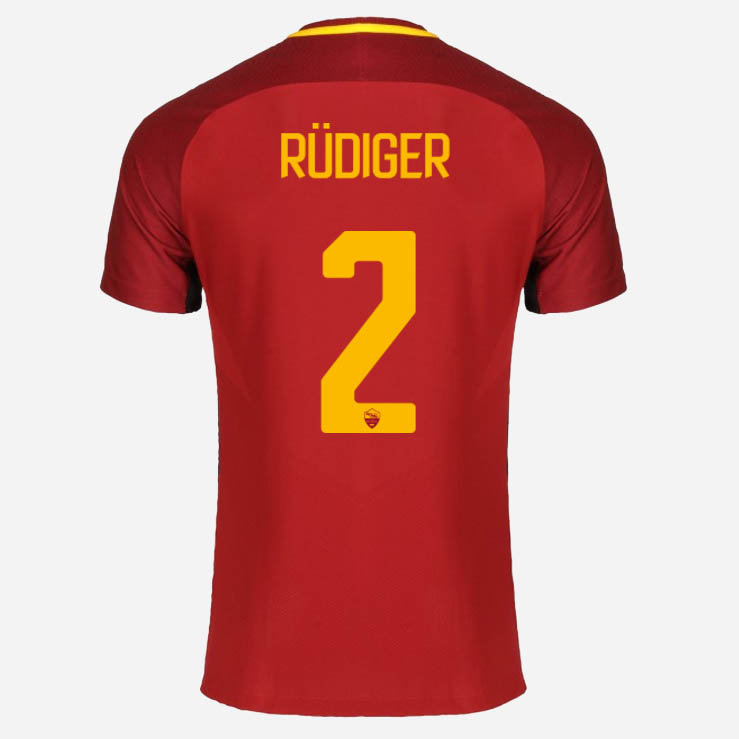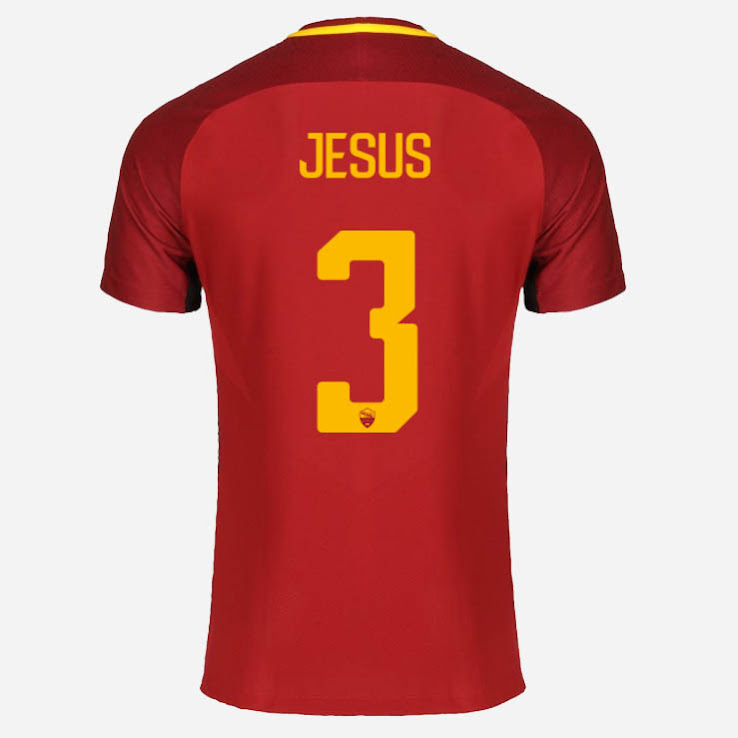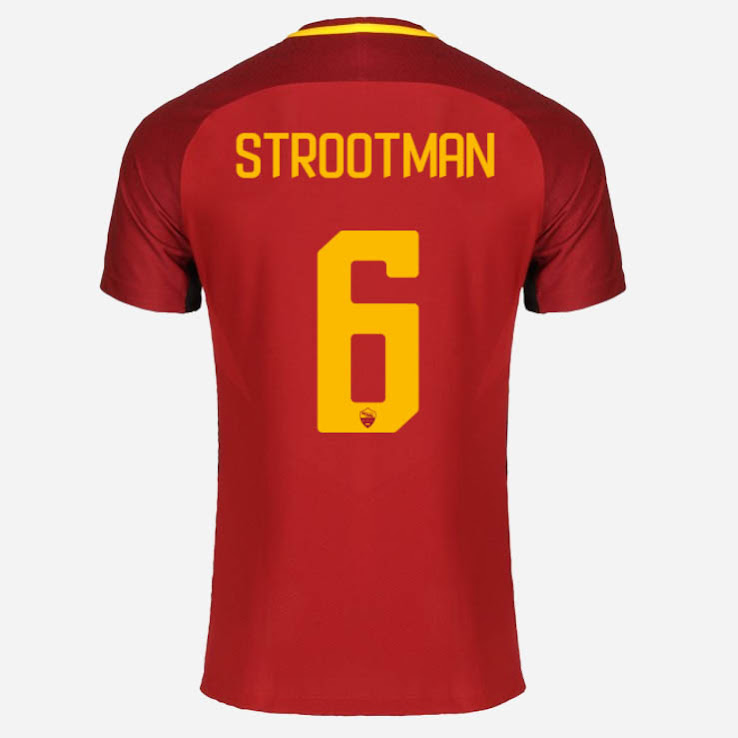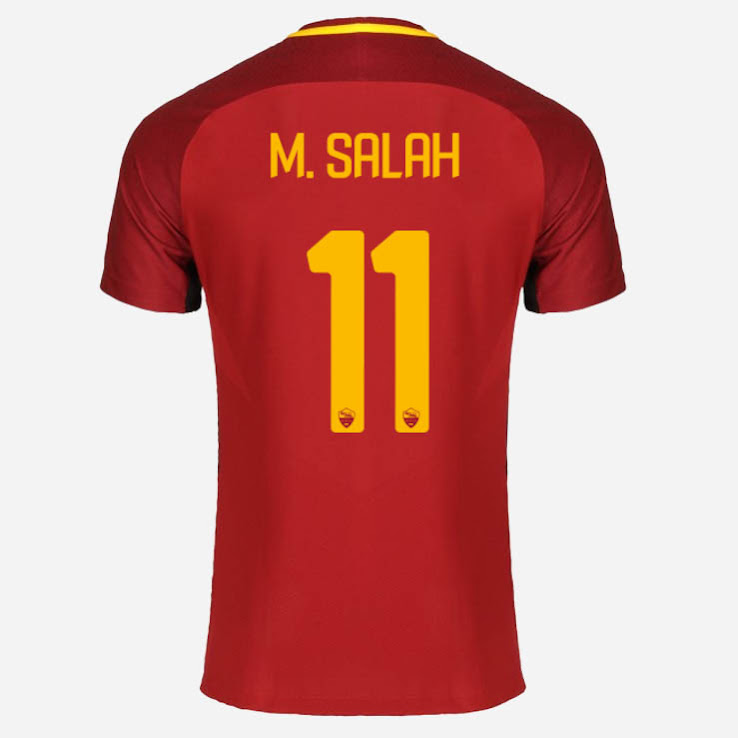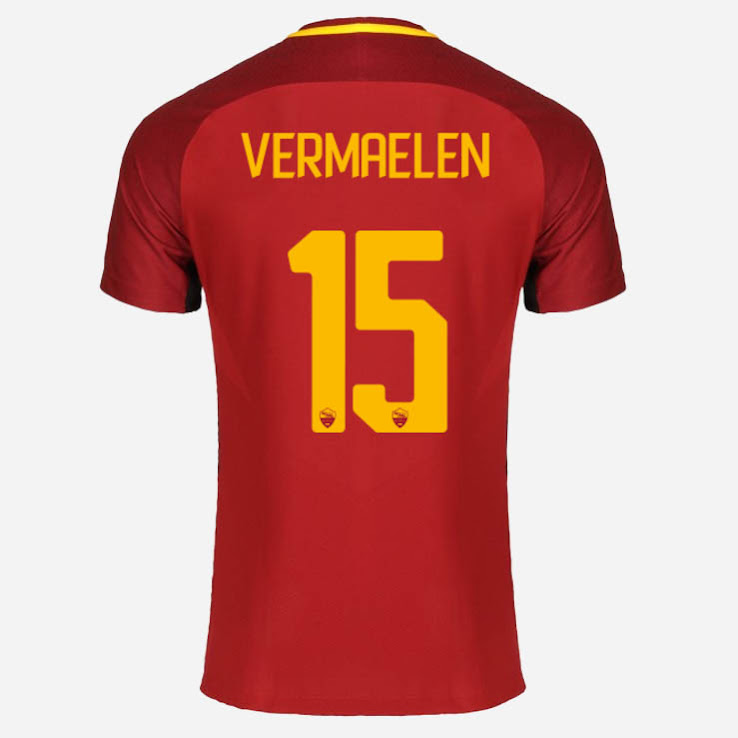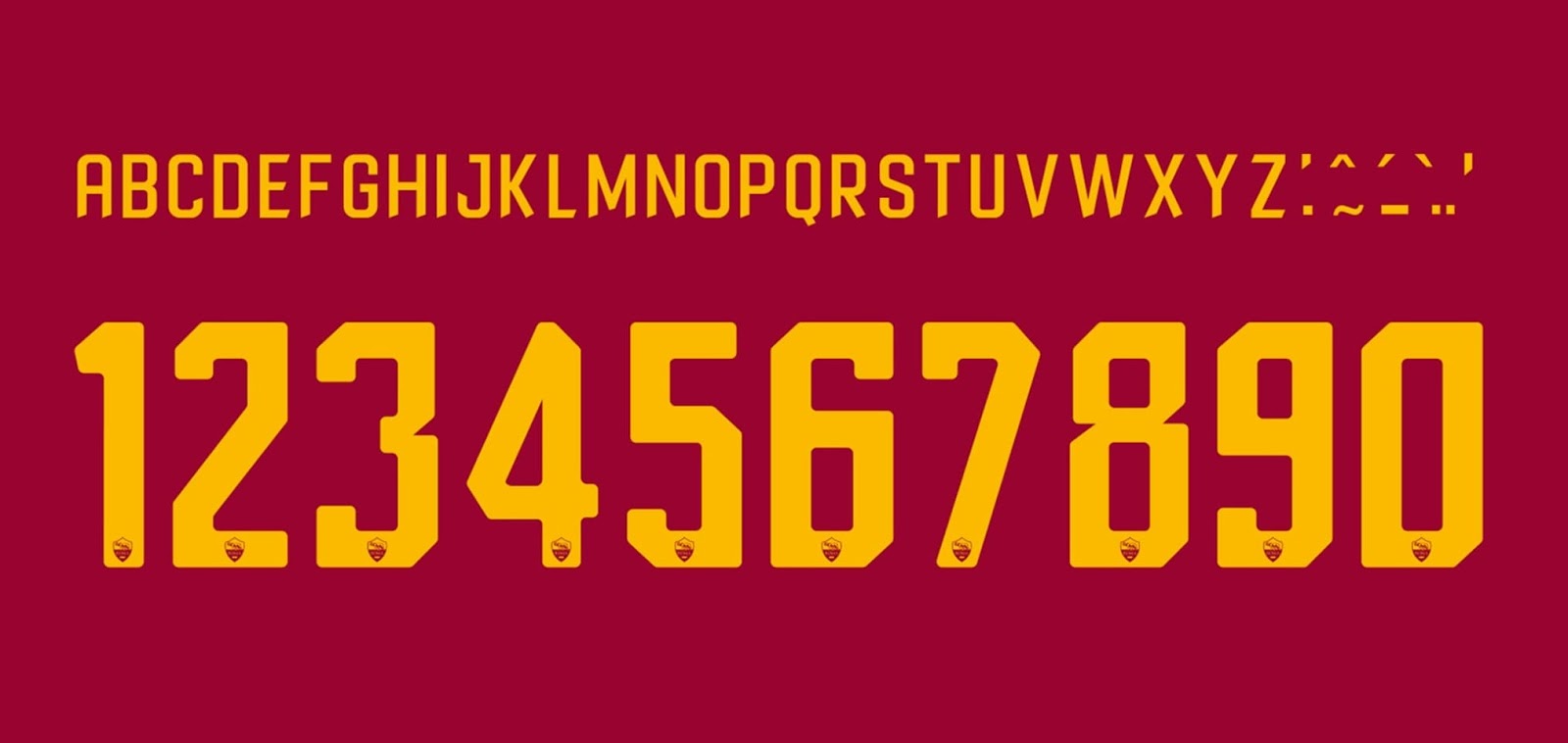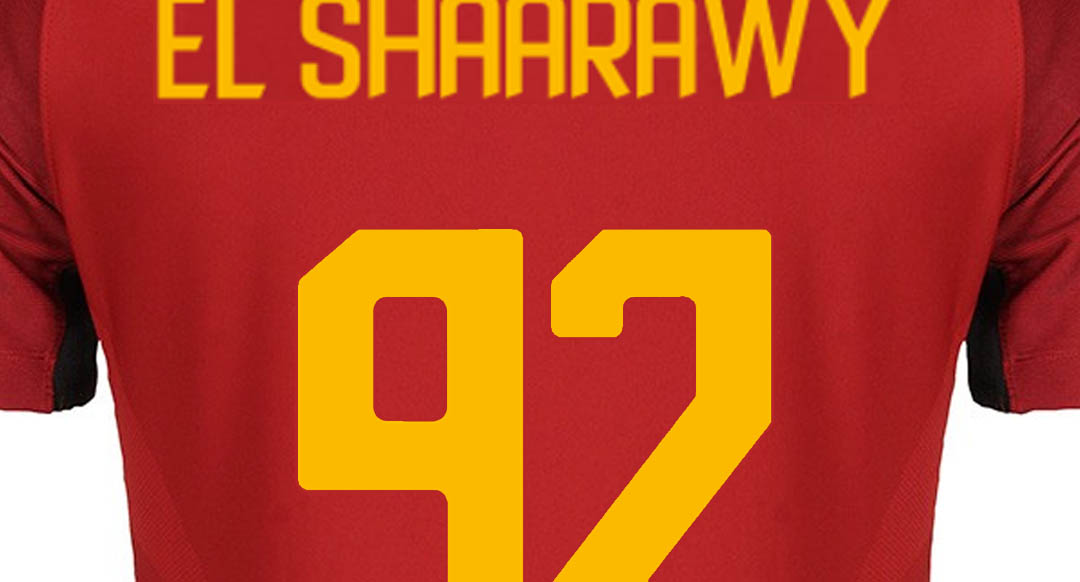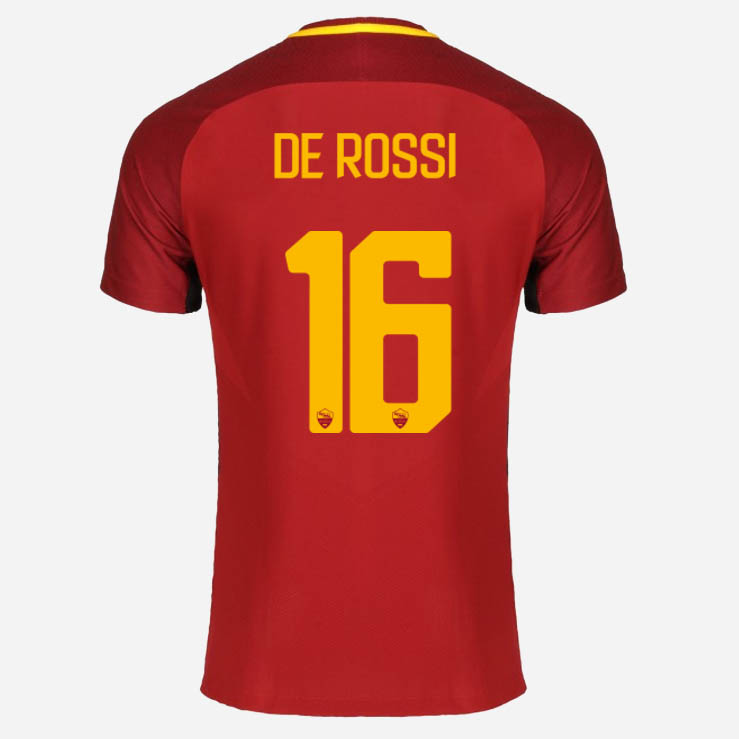
Einzigartige AS Rom 17-18 Trikot-Schriftart veröffentlicht
Die neue AS-Rom-Schriftart für die Saison 2017-2018 führt ein deutlich spezifischeres Design als das saubere neue Rom Nike 17-18 Heimtrikot ein.
Rom 17-18 Trikot-Namen und -Nummern
Hier ist die neue Rom-Schriftart für die Spielzeit 2017-18.
Jede Nummer und Buchstabe der neuen AS Rom 17-18 Schriftart, die ein sehr außergewöhnliches Design hat, weist einen einzigartigen Look auf. Die Buchstaben und Nummern sind orange. Die Nummern setzen am unteren Ende auf AS Roms Wappen.
AS Roms neue Schriftart für die Saison 2017-2018 wird auch für die neuen Auswärts- und Ausweichtrikots des Klubs verwendet, die zu einem späteren Zeitpunkt enthüllt werden.